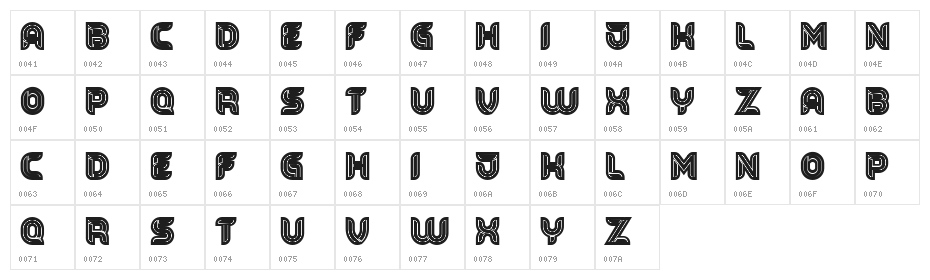
Speed Regular Font
| Gesamtstil | Retro-Futuristic |
| Vorgeschlagene Projekte | Ideal for posters, logos, headlines, and any design requiring a bold, dynamic typeface. |